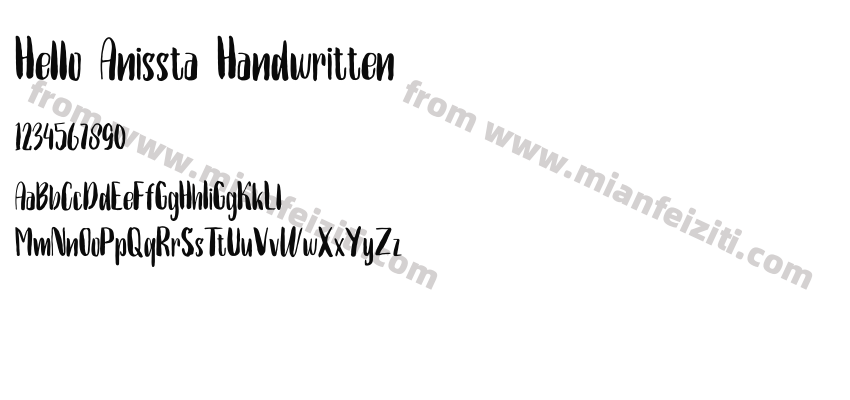
Hello Anissta Handwritten
字体名称: Hello Anissta Handwritten
Postscript名称: HelloAnissta-Handwritten
字体字重: Handwritten
本款“Hello Anissta Handwritten”是一款书写很新颖的字体,字体大方,适合各种设计作品使用!欢迎下载!